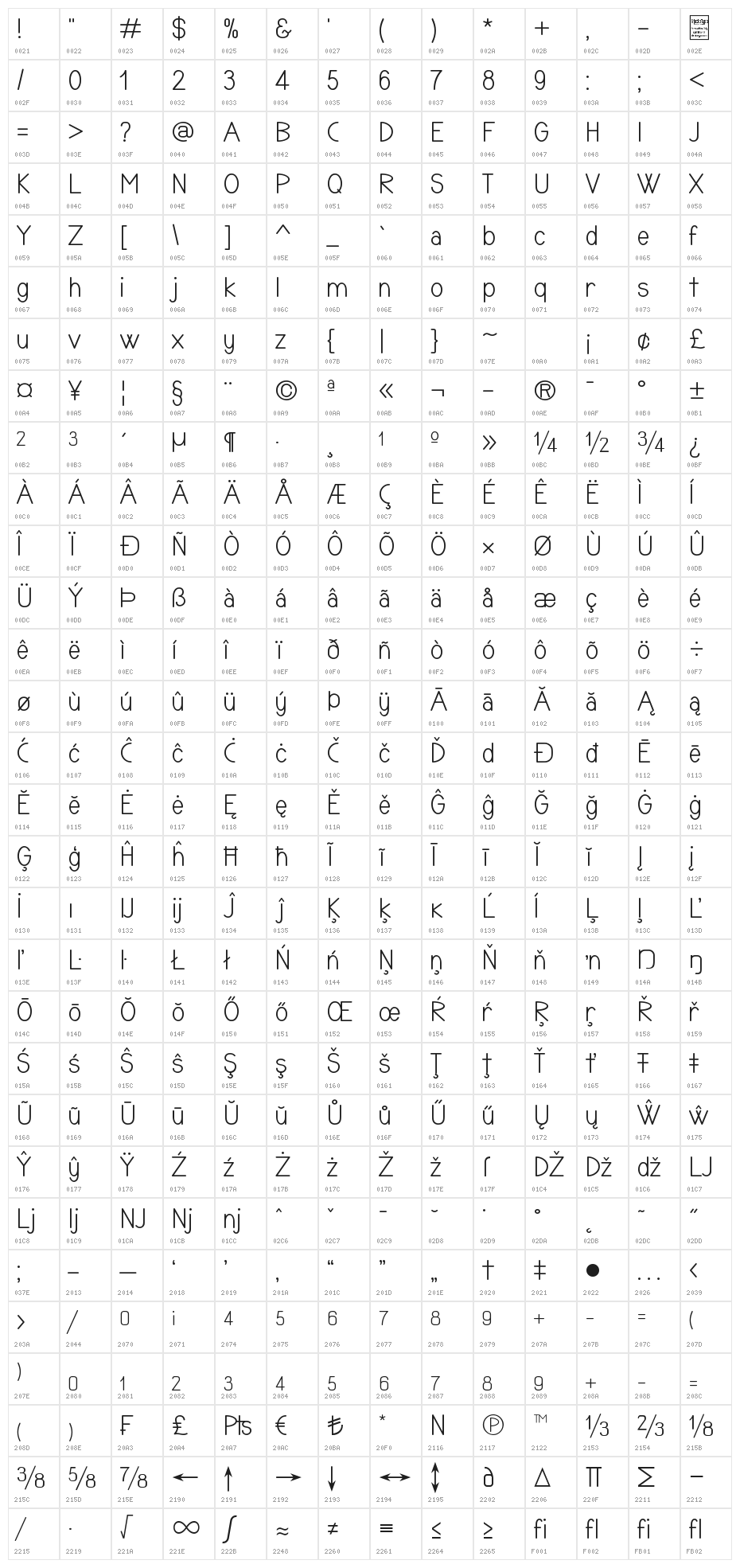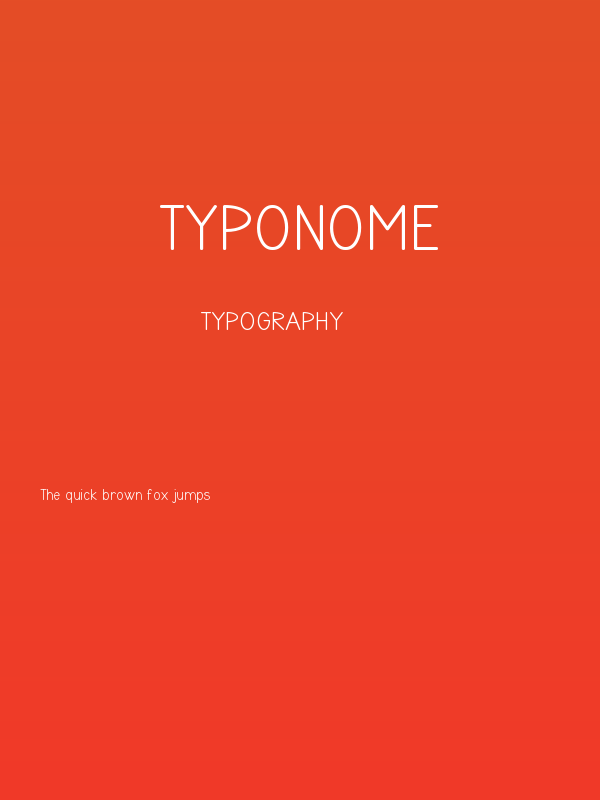
TYPONOME Font
| Kategorien | Sans Serif |
| Anwendungsfall | Headlines, Body text, Logos |
| Vorgeschlagene Projekte | Ideal for branding, web design, advertising, and editorial projects where a modern and clean aesthetic is desired. |